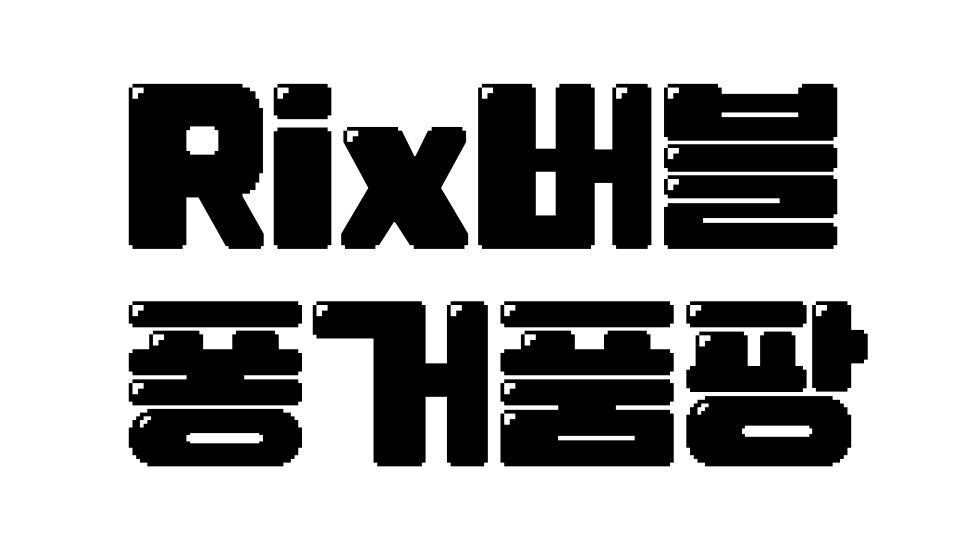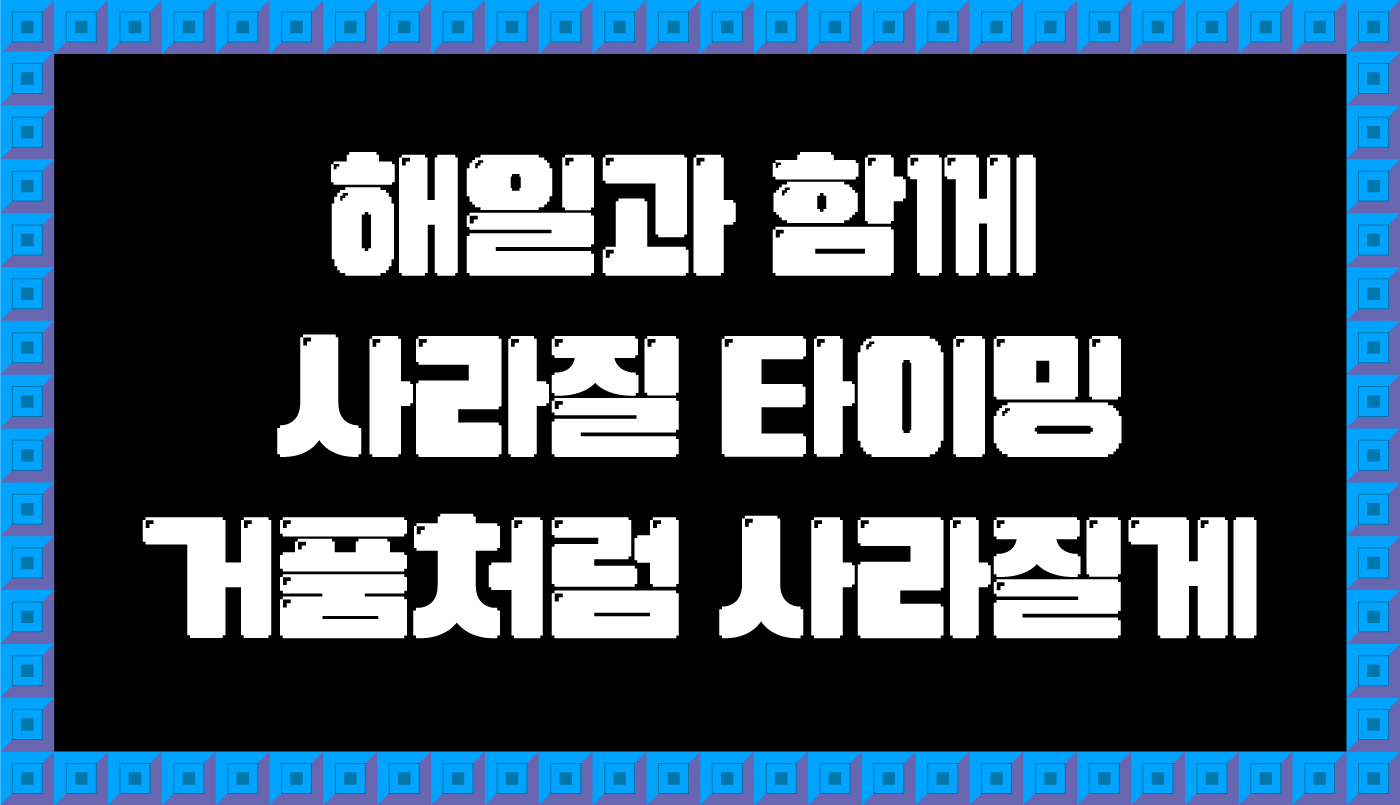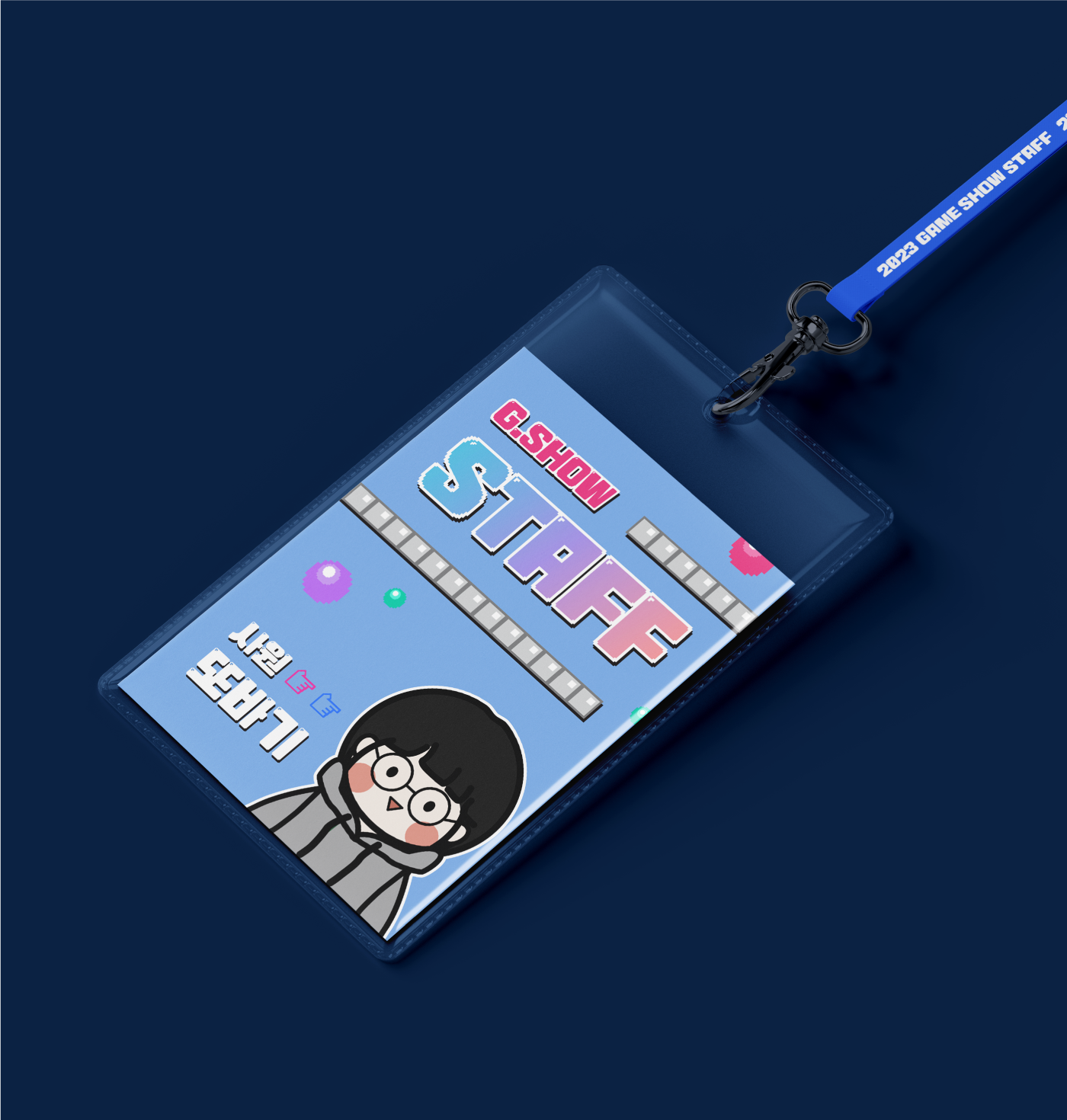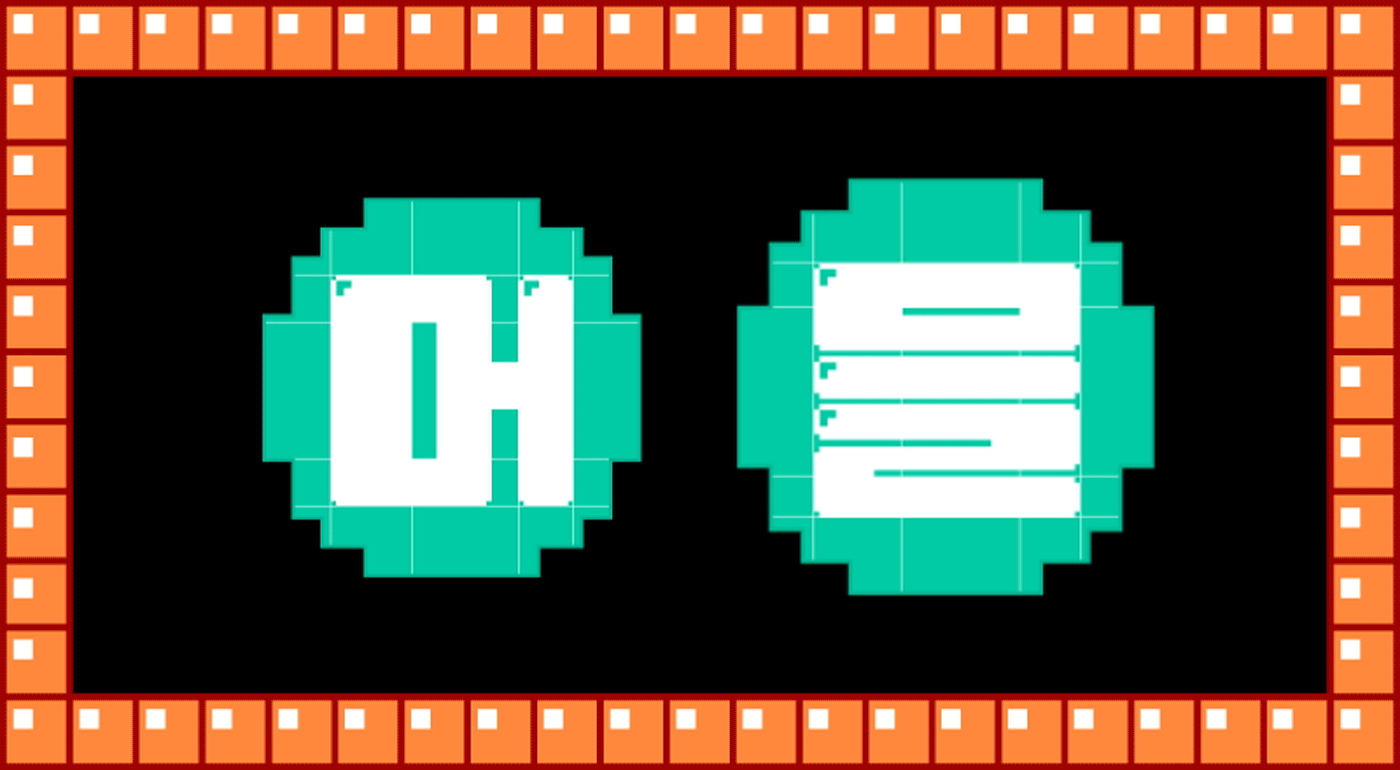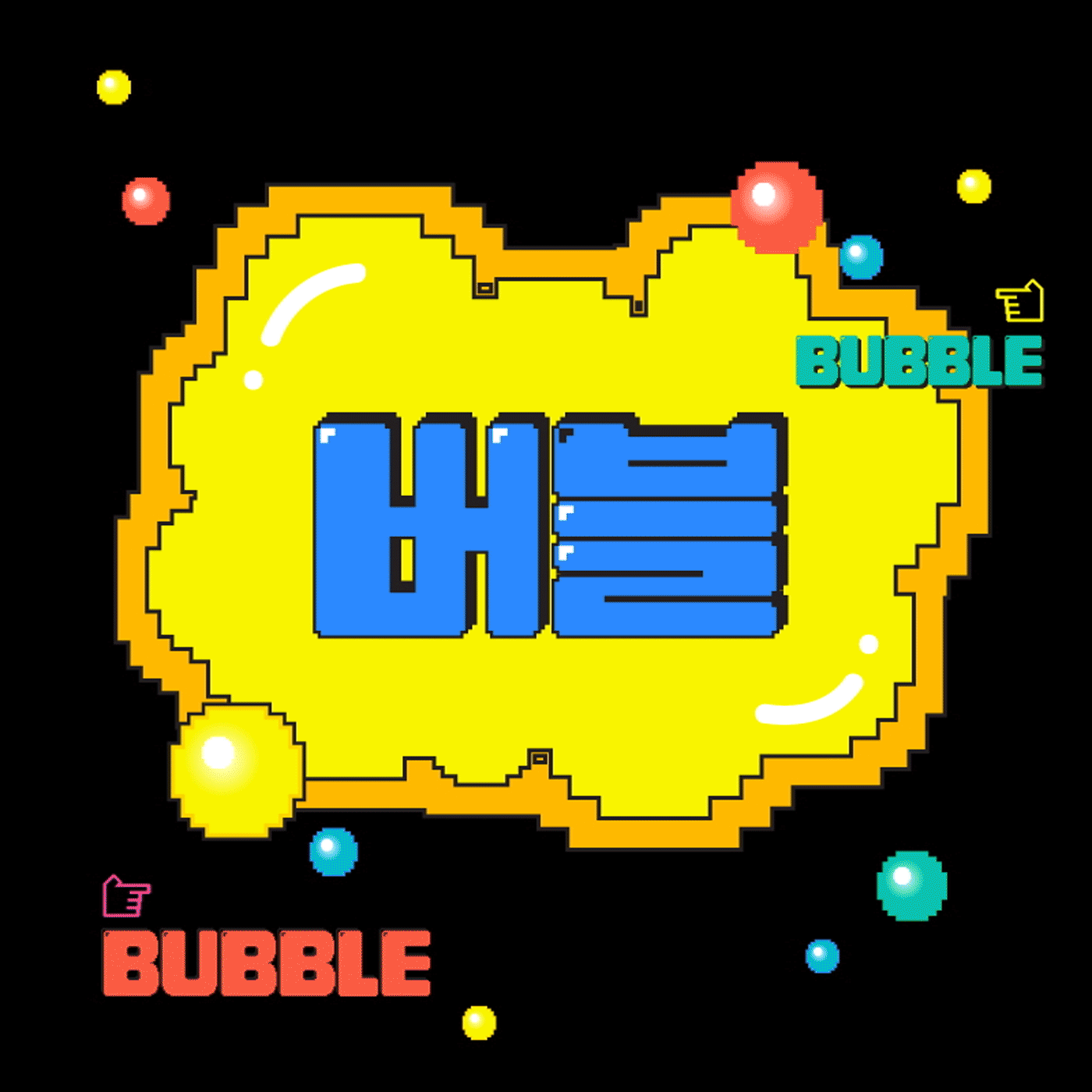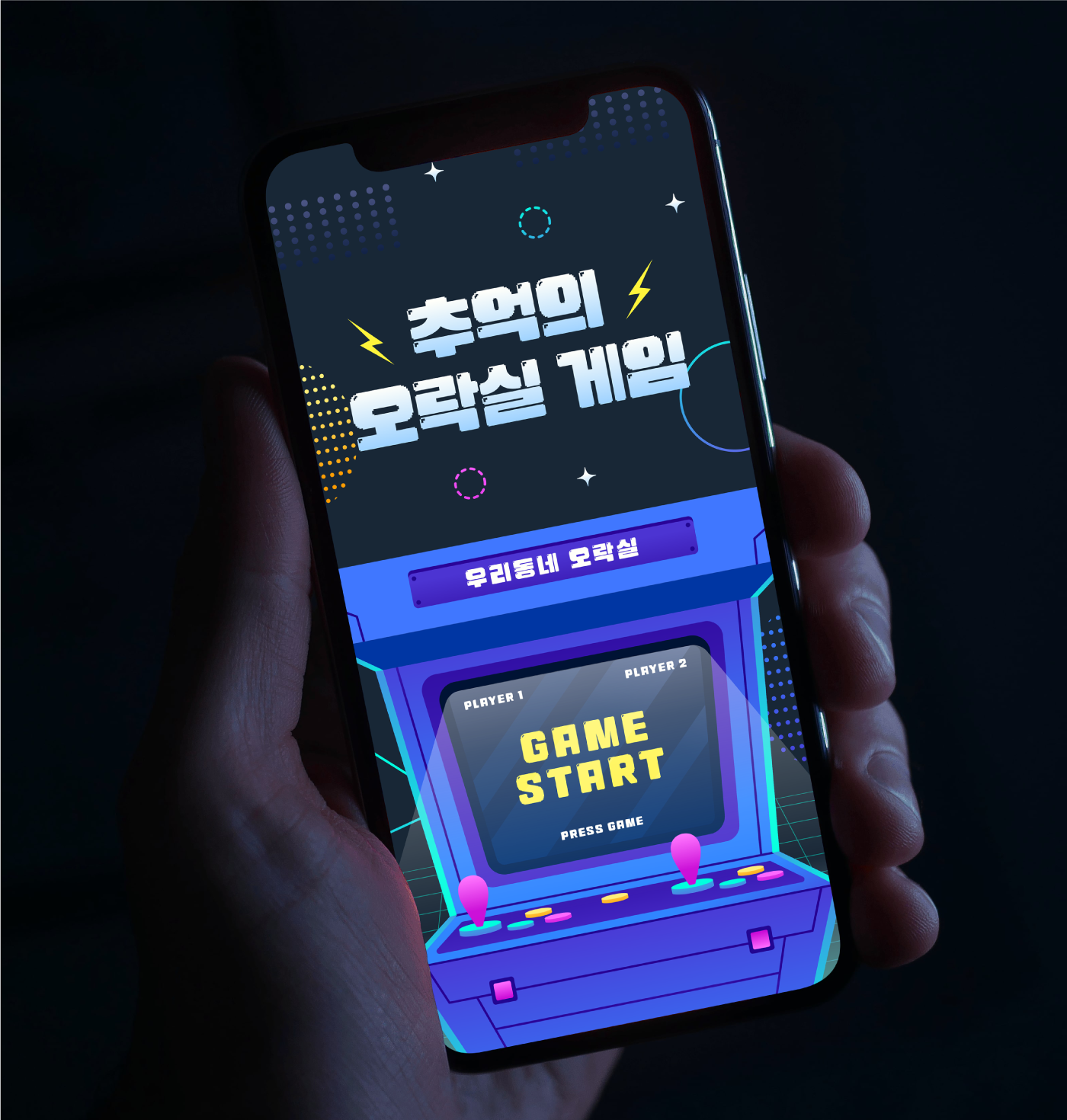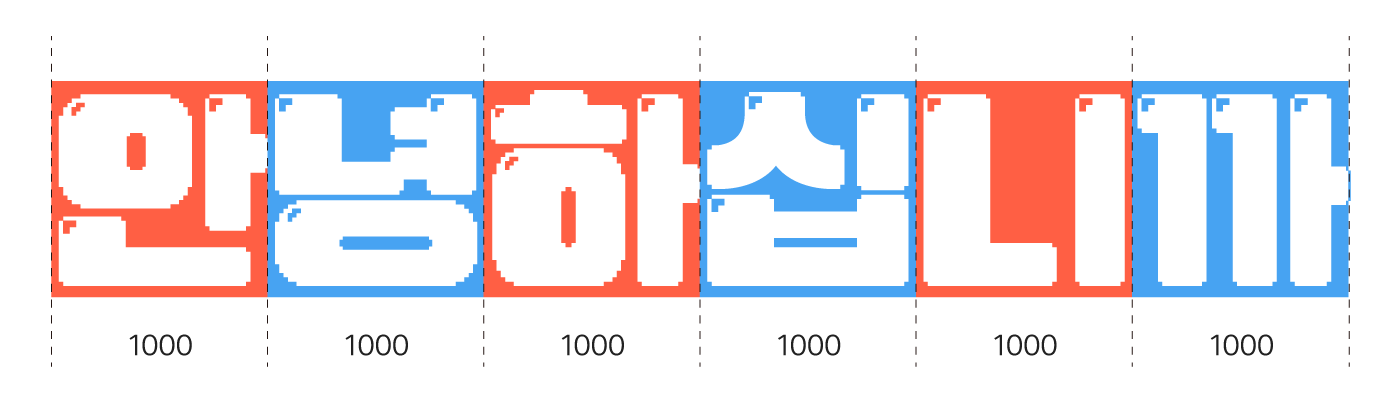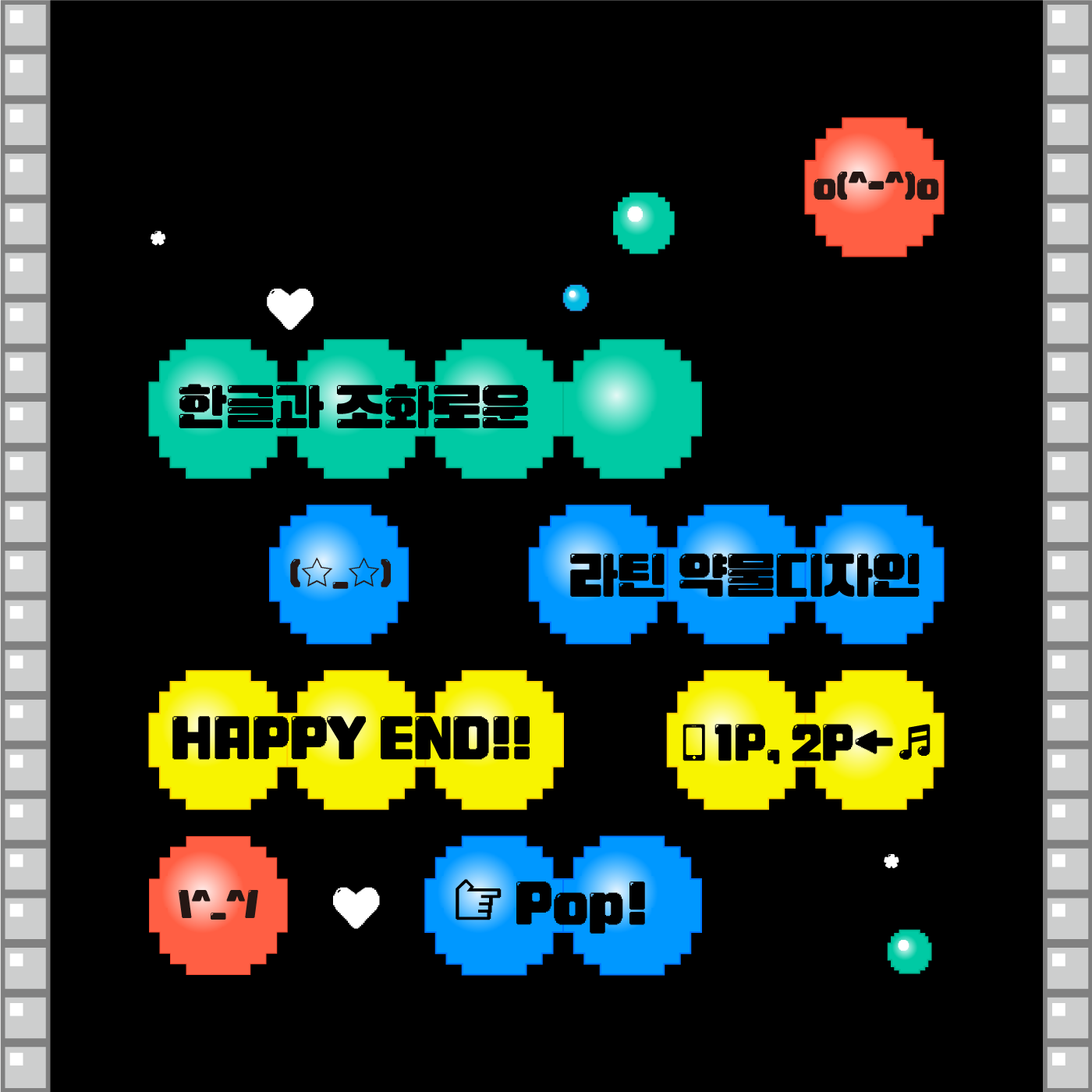
안녕하세요. 선선한 바람이 불어오는 10월, 가을의 신규 서체 「Rix버블」을 소개합니다! 한눈에 귀여움과 즐거움이 팡팡 터지는 이번 폰트는 픽셀 디자인이 들어간 유니크한 헤드라인 서체입니다. 이번 폰트를 제작한 유현주 디자이너와의 인터뷰를 통해 폰트에 대해 좀 더 자세히 알아볼게요 :)
안녕하세요. 오랜만의 인터뷰인 것 같아요! 간단히 소개와 근황 부탁드립니다.
안녕하세요. 최근에 윤유민 프로님과 Rix콘트라스트 작업을 마치고 Rix버블로 인사드리게 되었습니다. 폰트 출시는 꾸준히 한 것 같은데 인터뷰는 오랜만이네요!
그러게요, 이번에 기획하신 Rix버블은 어떤 폰트인가요?
Rix버블은 최근 유행했던 Y2k 컨셉을 겨냥해 제작된 폰트입니다. 픽셀 폰트에 관한 레퍼런스를 찾아보다 보니, 2D 형태에 얇거나 표현이 간단한 경우가 많아 좀 더 귀여운 맛을 가미하고 싶어 획 두께를 가변적이게 했고, 글레어 픽셀을 추가해 두께에 어울리는 양감을 더해주었습니다.
작업 시 영감을 얻었던 것이 있다면.
픽셀 그래픽에 관련된 레퍼런스를 찾아보다가 어렸을 때 했던 게임 중에 보글보글(지역마다 이름이 다르더라고요..? 보글보글 보블보글,, 저는 보글보글이라고 불렀던 기억이 있네요🙂)을 메인 레퍼런스로 삼았습니다. 게임 중 등장하는 거품 방울에서 글레어 표현을 추가해야겠다고 생각했어요.
이번 신서체, 이렇게 활용하면 좋겠다!
Rix버블은 최근에 릭스에서 출시한 폰트들이 대부분 강한 느낌이 대부분이라 귀여운 컨셉에 가볍게 쓸 수 있는 폰트로 기획했어요. 획에 작은 표현들이 많아 긴 문장들에는 적합하지 않고, 영상 컨텐츠의 짧은 자막이나 제목에 사용되기를 희망합니다ㅎㅎ 귀여운 효과 자막으로 써주세요..!
폰트 디자이너로서 일하고 계신데, 본인 직업의 #단짠이 뭐라고 생각하시나요?
모든 디자이너들이 똑같겠지만 새로운 걸 계속 기획해야 한다는 부담이 크게 다가올 때가 있는데, 길을 지나가거나 방송에서 유튜브에서 가끔 제가 만든 폰트가 보이면 뿌듯..? 하다고 해야될까요ㅎㅎ 신기하기도 하고.. 최근에 Rix콘트라스트를 같이 작업한 유민님이 발견하고 찍어주신 사진인데 종종 예상치 못한 곳에서 결과물이 눈에 띄는 게 재미있는 일인 것 같아요.
귀엽고 빵빵한 헤드라인
2000년대 초반 오락실 게임 속에서 튀어 나온 듯한 폰트, Rix버블! 네모꼴 꽉 찬 형태와 두꺼운 획, 둥글둥글 꺾임이 귀여운 픽셀 폰트입니다.
가로 1000 unit의 고정 자폭으로 설계되어 넓고 꽉 찬 공간감을 느낄 수 있습니다. 굵은 획의 두께가 무거워 보일 수 있지만 불규칙적인 획의 대비로 리듬감을 주어 무게를 덜고 재미있게 표현했습니다.
그 시절 픽셀 폰트의 진화
Rix버블은 자소 끝부분의 반짝이는 글레어 표현으로 버블의 입체감을, 또 꺾임 부분의 픽셀 표현으로 픽셀 폰트의 특징을 최대한 살려 디자인했습니다.
픽셀 폰트는 말 그대로 글자를 확대해서 보면 픽셀(디스플레이에서 가장 기본이 되는 화면 최소 단위)로 이루어진 폰트를 말합니다.
피처폰을 쓰던 시절에 많이 봤던 폰트죠! 요즘 Y2K , 레트로가 다시금 주목을 받고 있어 픽셀 폰트에 대한 관심도 커진 것 같아요. 릭스폰트의 Rix전자오락 폰트나 둥근모꼴+Fixedsys처럼 90년대에 쓰던 비트맵 글꼴을 현대에 맞게 재배포한 폰트도 있습니다.
이러한 픽셀 폰트들은 아무래도 기존의 디자인에서 크게 벗어나지 못하는 경우가 많은데, Rix버블은 가변적인 획 두께와 글레어 표현, 입체감 등으로 현재의 트렌드나 콘텐츠에 더 활용하기 좋은 진화한 모습의 픽셀 폰트로 제작했습니다🫧
이렇게 활용해 보세요🎮
오락실 게임에서 영감을 받은 만큼 아무래도 그와 연관된 모바일 게임이나 웹페이지 등 흥미롭고 귀여운 레트로 컨셉 디자인에 활용하기 좋습니다.
디자인적으로 유니크한 포인트가 필요하다면? 캐주얼하고 유쾌한 감성으로 다양한 콘텐츠에 활용해 보세요 :)